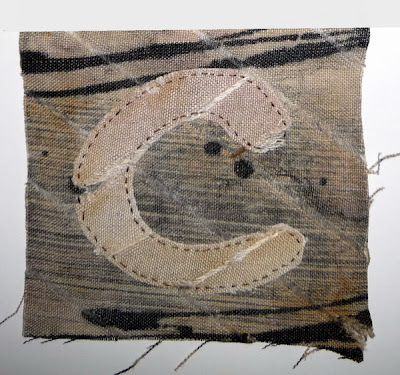
Voilà mes 4 lettres suivantes toujours, sur le thème de la paix avec de la légèreté et de la transparence !
Pour le "J", j'ai utilisé le papier à bulles dont on se sert pour envelopper les objets précieux.
Here are my four following letters always on the theme of peace with lightness and transparency!
For "J", I used the bubble wrap that is used to wrap valuables.